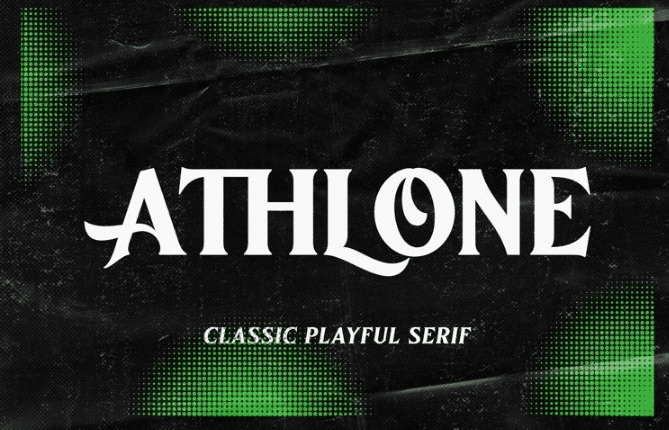
Название: Athlone Font | Vintage Seri
Представляем Athlone, шрифт дисплея, вдохновленный винтажными/классическими буквами.
Мышь выполнена с большим вниманием к деталям; чистые линии, острые края и заманчивые изгибы.
Доступна и в наклонном варианте, дает вам больше возможностей для игры.
Лучше всего подходит для заголовков/заголовков, логотипов/логотипов, дизайна упаковки/этикетки и т.д.